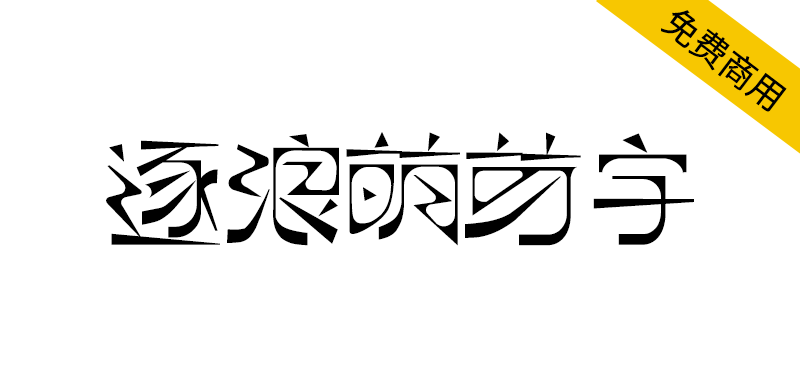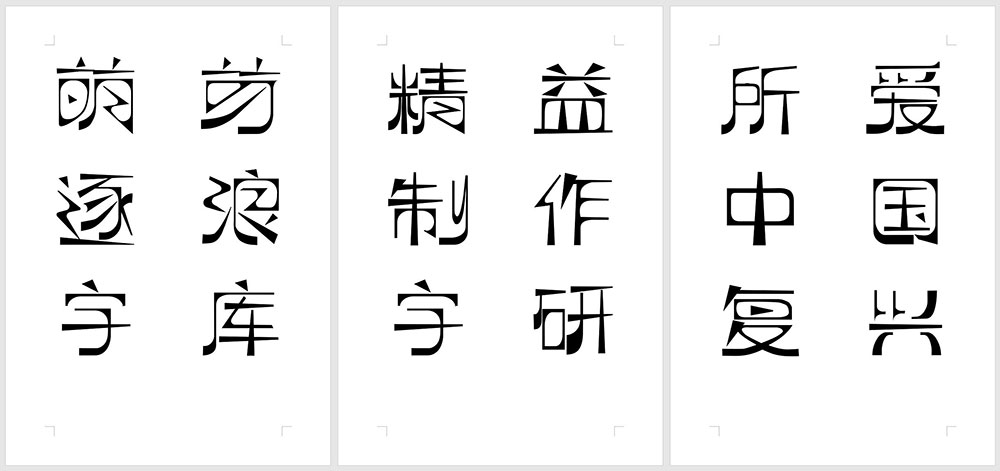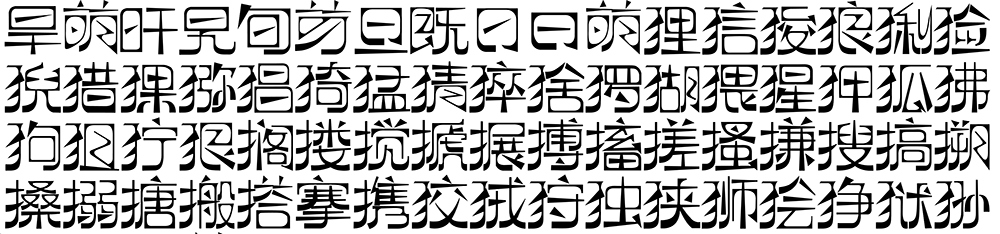
逐浪萌芽字是一款参照借鉴近代中国共产党《萌芽》月刊的艺术字体,源自五四运动文化,力求体现近代文艺风。逐浪萌芽字是一套优秀的中文字库,逐浪字库团队出品,中文字形部份符合中华人民共和国GB2312规范,英文与拉丁字形符合GoogleFonts开源规范。
字体线条呈现外方内圆格局,有尖锐的外角、三角部件,而内部空间则呈现圆形切割效果。这体现了五四、清末民初,在工业革命思维冲击下,一代文化人对于中国汉字的探索。又似布尔什维克人的工人、工业文化在汉字下的体现。尖锐、锐角三角形的部件,从中体现了上进、革命、进击。结字扁形,即左右宽度大于上下高度。
○ 外角采用尖角,内角采用弧角
○是一个抽象的孤形字。
○试图创造上个世纪30年代“左联”的手写字体风格,该风格是用于出版物出版,简朴又不失艺术性。
○多弧形、多三角形。
○整体偏矮宽方正型,非常规字体,异型字居多
○笔画粗细对比明显,角的笔画相对横竖线要粗
○竖线笔画下端粗上端细,横线笔画左边粗右边细
○外角整体偏方形,内角整体偏圆形的创意字体
○整体风格硬朗纤细
创作笔记:一款字体,从前期创意,到基本造型,再到合成编程,再到优化出版。最少需要3-5个月。同时发布后还要针对各个场景进行修正优化,这是一个漫长的过程。所以中国古代有“仓颉造字,鬼神哭”的说法。